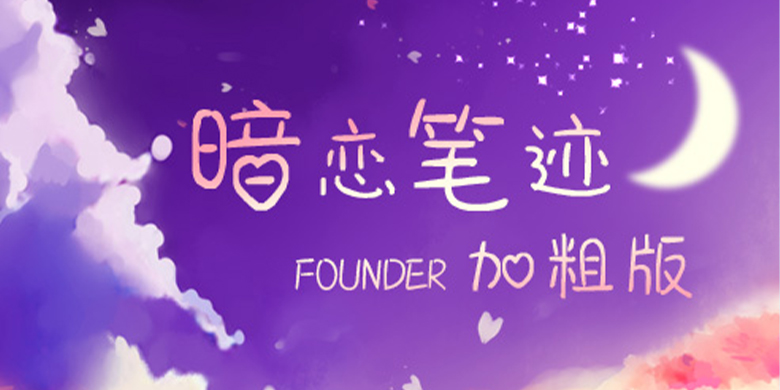
方正手迹-暗恋笔迹加粗版
方正手迹-暗恋笔迹加粗版,这款字体结构工整、笔画清晰,兼顾美观与易读性,适用于标题、正文、海报、包装、LOGO 等多种场景。字形优雅稳定,风格百搭耐看,适配日常排版与创意设计,让文字呈现更舒适、更具质感。方正手迹-暗恋笔迹加粗版一笔一画,皆是细节,以均衡的比例、流畅的线条打造舒适视觉体验,字形端正大气,风格简约现代。无论是商业设计、品牌宣传还是日常排版,都能轻松驾驭,让文字更有格调与力量。方正手迹-暗恋笔迹加粗版字体下载。
宽松的中宫,简洁的笔画,轻松大方的字形,圆润的转角处理,温婉迷人,加上化“口”为爱心,简直是少女气息满满,阅读起来有心动的感觉。适用于少年儿童类的书刊、品牌广告和产品包装设计,以及社交网络的个性化用字。